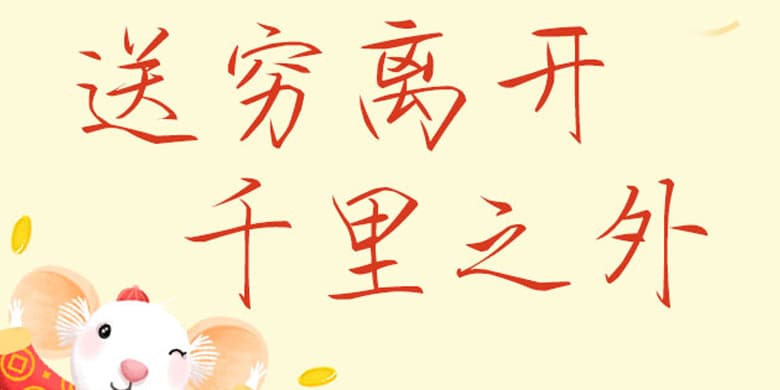
品牌:方正手迹设计师:刘殿儒发行时间:2020字库编码:简繁扩展(GBK)分类:常规书写·硬笔字体属性:精品字
送穷离开千里之外这款字是一款行书风格手写体,笔画粗细变化较大,字迹洒脱秀气,现代的简约中又参杂着些许古典书法感觉,让人赏心悦目。适用于文艺类的书刊、品牌广告和产品包装设计,以及社交网络的个性化用字。